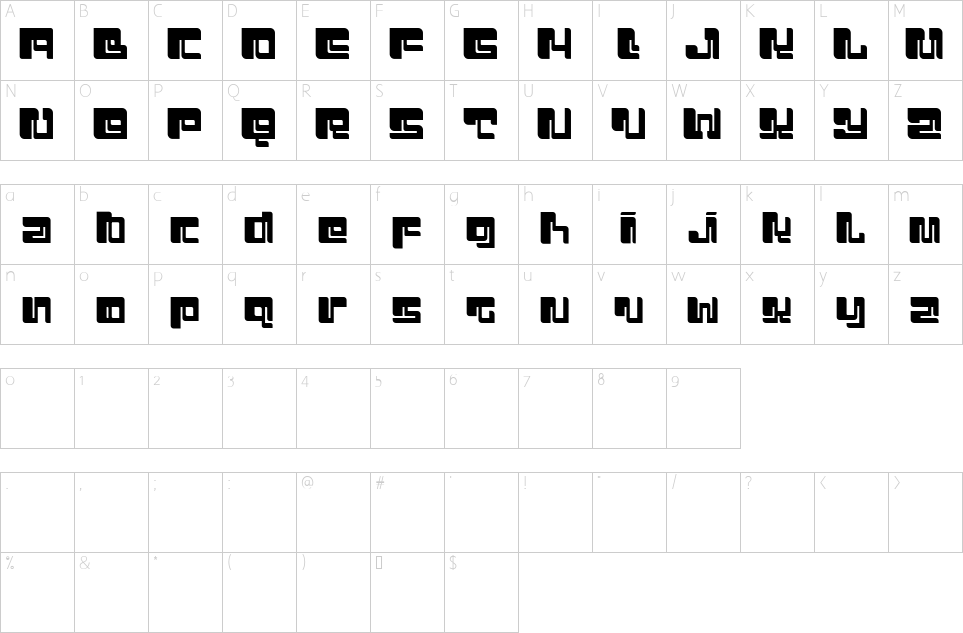
Punk Cyber Font | 1001 Free Fonts – Fonte Grátis
A fonte Punk Cyber está disponível em sua versão grátis para Windows e Mac, criada pelo designer desconhecido da Dharmas Studio. Seu estilo inovador e futurista é perfeito para criar textos de graça e humor, especialmente em designs de tecnologia, internet e cyberpunk. Este estilo único e criativo tem sido baixado 299 vezes, demonstrando seu valor na comunidade de designers. Adquira sua cópia agora e personalize o texto do seu próximo projeto de forma inovadora e única.